معرفی خطوط اسلامی- خط محقق
ریشه خط محقق به کوفی میرسد و توسط وراقان عراق و در زمان عباسیان و زمان مأمون ظهور یافتهاست و اولین خطی است که مورد تهذیب و هندسیکردن ابن مقله قرار گرفت. خط محقق یک دانگ و نیم دور و چهار دانگ و نیم سطح است و از این لحاظ به خط کوفی نزدیک است. محقق، یکی از اقلام سته است که در آن، اشکال حروف یکدست، یکنواخت و درشتاندام است و با فواصل منظم و بدون تداخل نوشته شدهاست. رواج خط محقق در دوران ابن بوّاب بودهاست. خط ریحان از خط محقق اقتباس شدهاست. قط قلم در محقق، محرفتر از ثلث است و حروفش نسبت به ثلث از تنوع کمتری برخوردار است. لازم به ذکر است که در برخی از نمونههای خط محقق، گاه حالتهایی از ثلث دیده میشود و گاه خط ثلث برخی از ویژگیهای محقق را در خود دارد. علائم و ضمائم خط محقق به شکل ظریف و ساده است و علامتهای تزیینی بسیار ساده دارد.
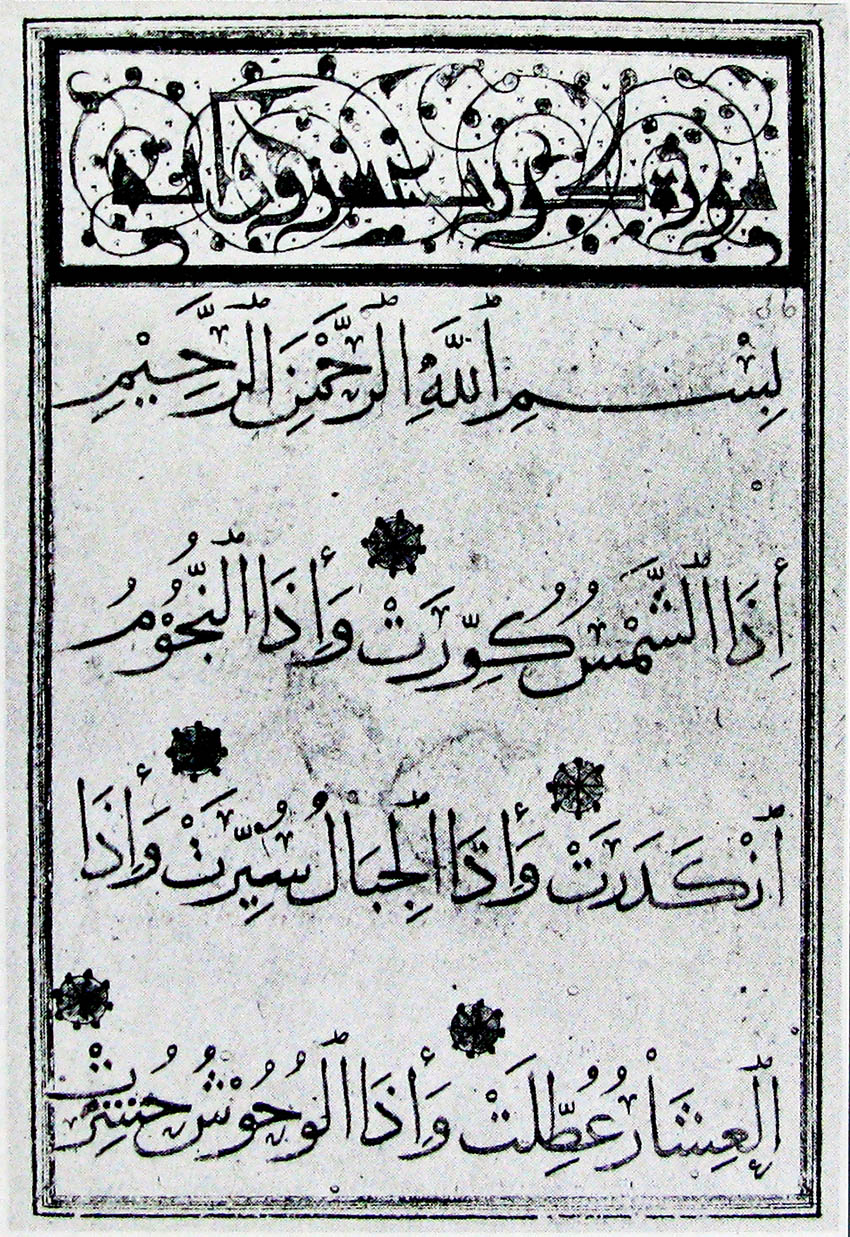
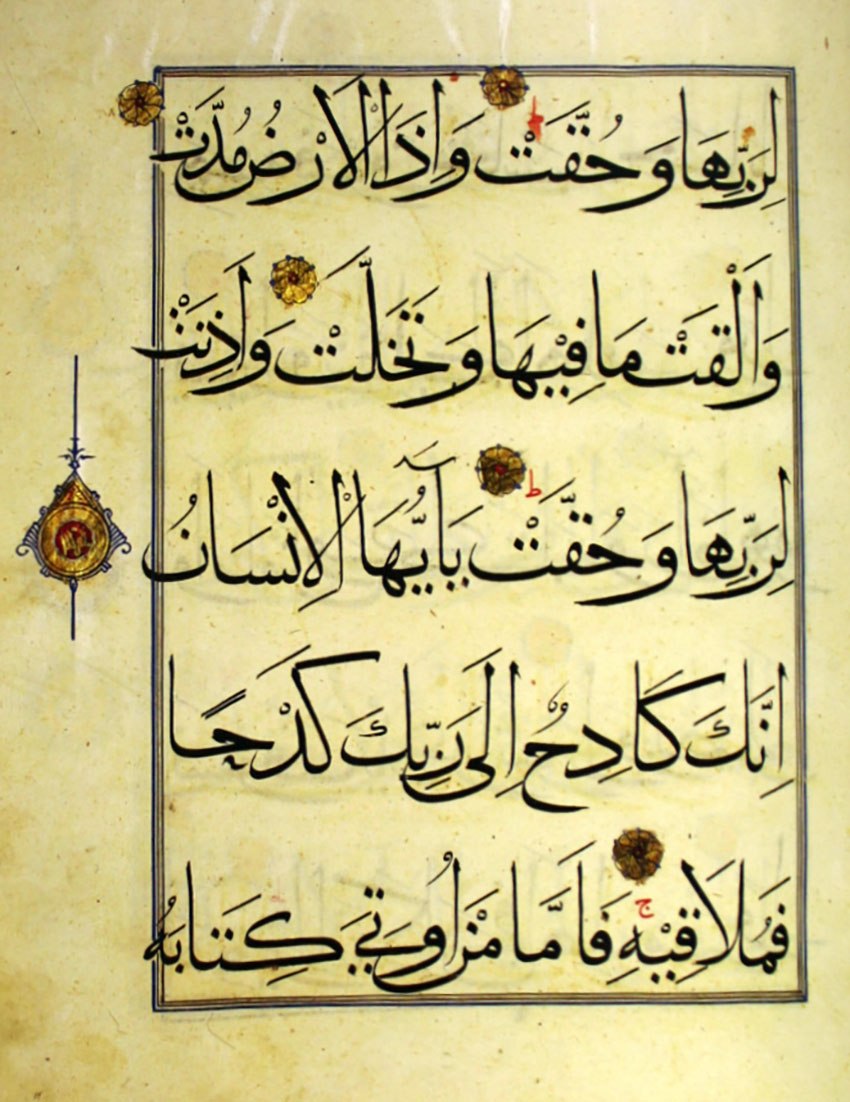
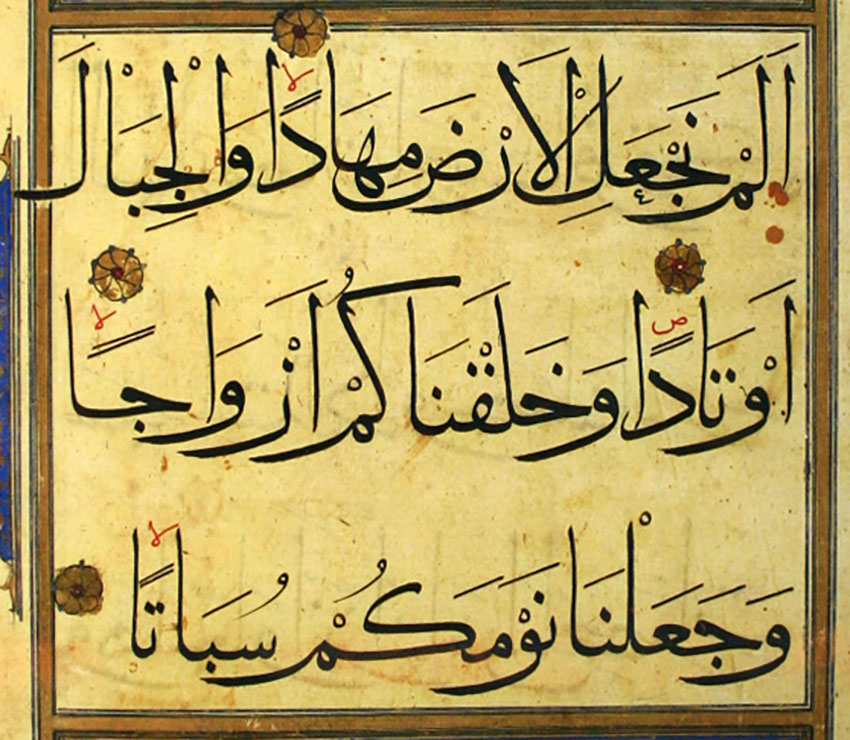
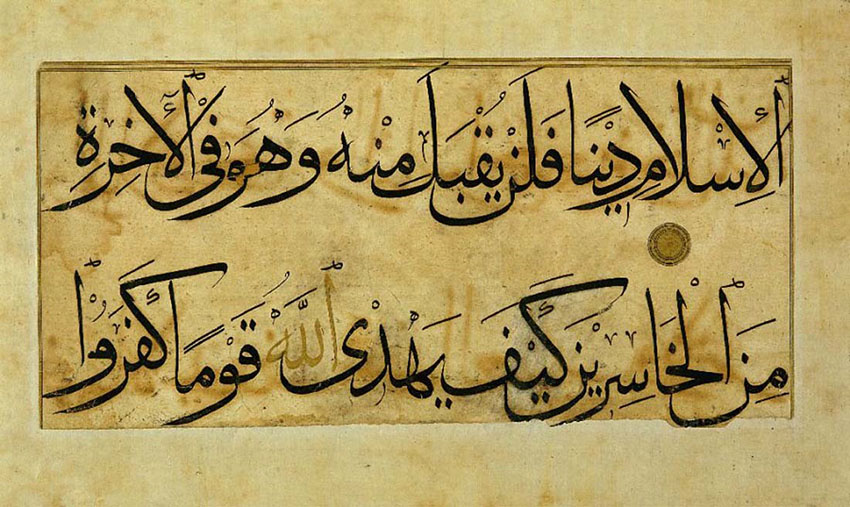
خط محقق، ساده و واضح نوشته شده و ترکیبات پیچیدهای ندارد و خطی خوانا است که اغلب برای کتابت قرآن به کار میرود و بهدلیل شکل کرسیبندی و سادگی حروف از خوانایی زیادی برخوردار است. در ادامه مهمترین ویژگیهای خط محقق ارائه میشود.
مهمترین ویژگیها
مهمترین ویژگیهای خط محقق عبارتاند از:
غلبه سطح بر دور
در خط محقق، سطح حروف بیشتر از دور آن است. دوایر «ن» و حروف مشابه آن از دور اندکی برخوردارند.
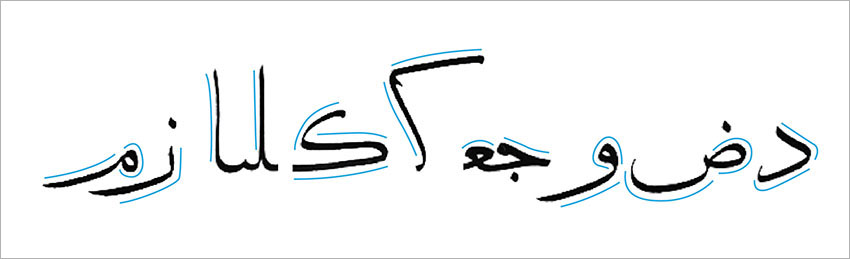
طُره (ترویس)
در خط محقق، «الف»ها با طره (ترویس) و به اندازهای بلند نوشته میشوند.
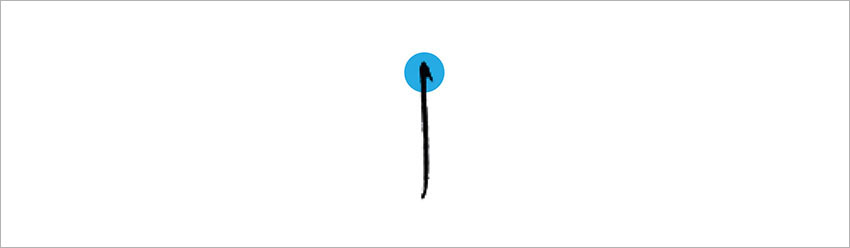
ارسال
حروف «و»، «ر» و «م» اغلب با ارسال نوشته میشوند. (ارسال، رها ساختن آزادانۀ قلم در هنگام نوشتن حروف است.)
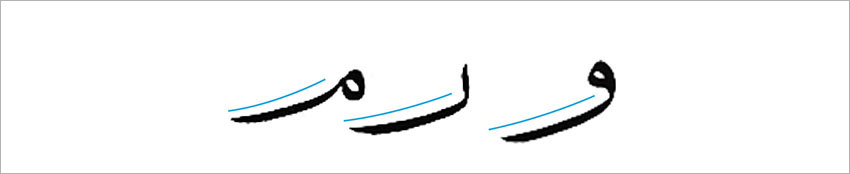
کرسیبندی
کشیدههای عمودی، بالاترین کرسی را تشکیل میدهند و سایر حروف اغلب حول کرسی وسط تجمع یافتهاند، یا به کرسی وسط نزدیک شدهاند. کرسی دوایر و حروفی مانند «ر» و «و» دارای عمق کمی است و به کرسی وسط نزدیک شده است. بنابراین سنگینی و تجمع کلمات و حروف بیشتر حول کرسی وسط یا خط زمینه است.
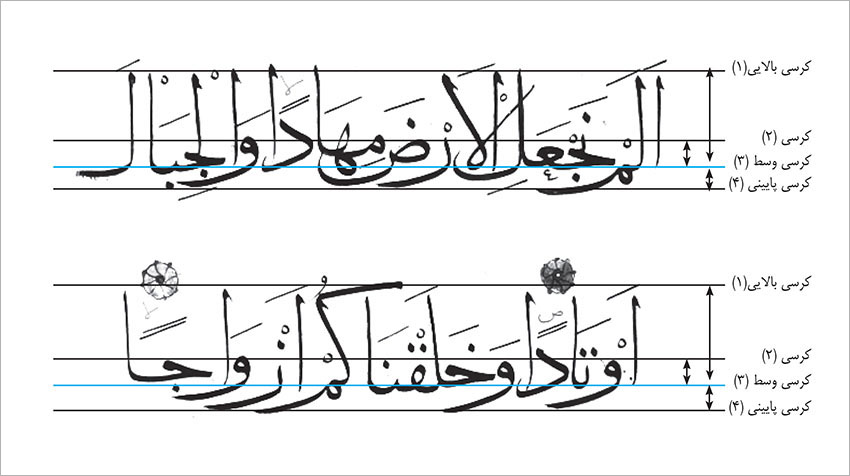
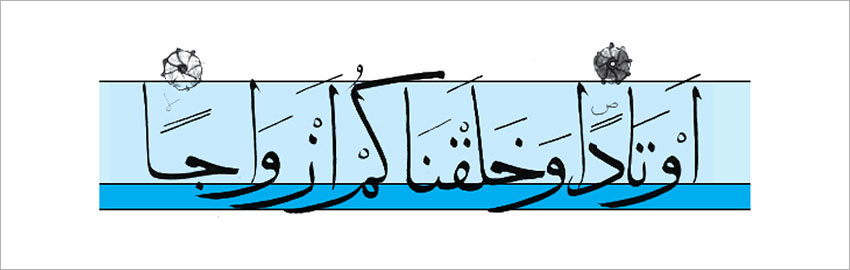
فشردگی فضای بین حروف
در خط محقق گاه حروف قبلی، فضایی برای حروف بعدی خود فراهم میآورند و در آن ریتم مناسبی بین «الف»ها و ارسالها ایجاد میشود. با این حال در این خط، حروف به صورت فشرده نوشته نشده و از وضوح کافی برخوردارند.
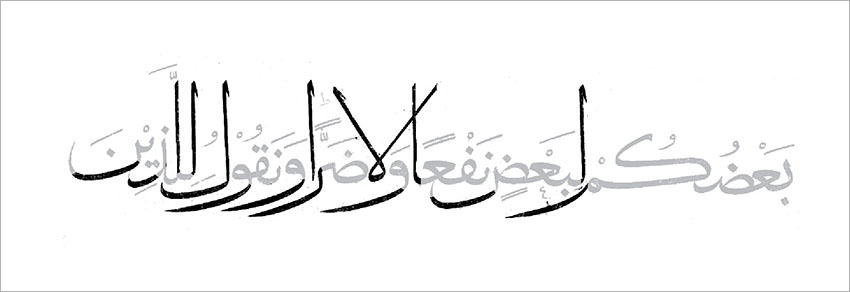
عوامل مؤثر در خوانایی
تنوع اندازۀ دندانهها، نوشتن حروف حلقوی با چشمهای باز و وضوح حروف از دیگر عوامل موثر در خوانایی خط محقق است.